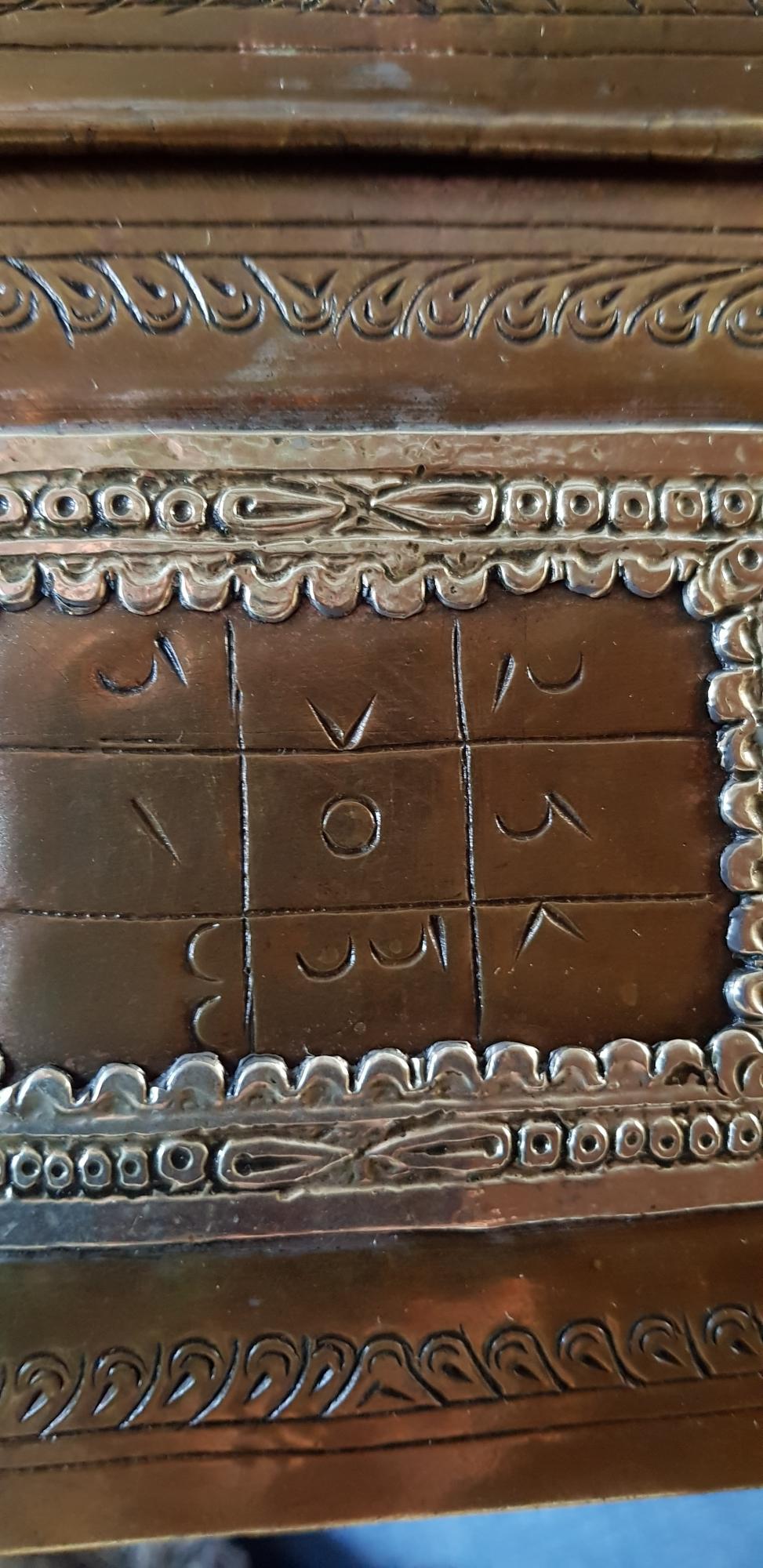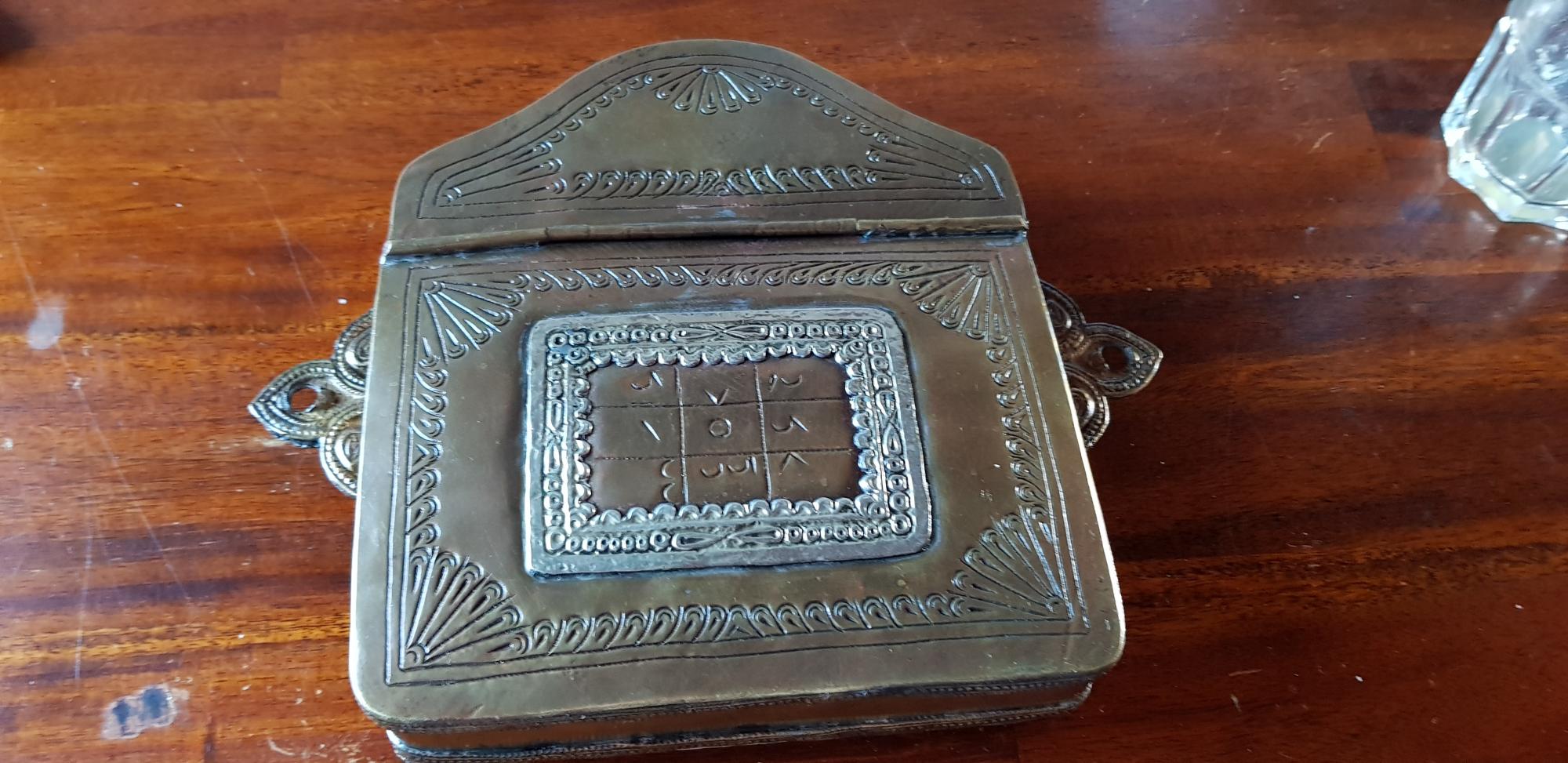
Wer kennt diese Schriftzeichen?
Ich suche jemanden,  der mir bei den Schriftzeichen helfen kann,  welche sich auch einer sehr alten "Box" befinden.  Weiß leider auch nicht so recht, was für ein Gegenstand es ist. Leider konnte ich auch nur diese beiden Bilder mit anhängen.
Leider bin ich nach langer Googlebefragung immer noch keine ansatzweise Lösung gefunden.
Aber vielleicht hat hier jemand eine Idee.
Hier noch zwei weitere Bilder.
Vielleicht helfen diese weiteren Bilder zur Erkennung.
Dieses Gegenstand ist auch von innen verziert mit Blatt und Blumen? Muster.
Ich sehe dort arabische Zahlen …
Hallo, ja das hatte ich auch vermutet,  jedoch fehlen da einige Schriftzeichen.
Das erste Zeichen, es hat noch einen zusätzlichen waagerechten Strich. Dann dieses uu strich. Auch wenn es ne zweistellige Zahl sein soll, was ist dann das 1ste u.
Ich lese dort
672
156
438
Soweit ich weiß, gibt es für die arabischen Zahlen unzählige Schreibweisen, je nach Herkunft, Schreiber, Volksstamm, Sprache und so weiter. Mal so wie es in meinem link dargestellt ist, aber auch gespiegelt, wie die 3 auf deiner Box.
Ralfs Vorschlag, das jemand Arabisch Sprechenden zu zeigen, kann aber sicher für Klarheit schaffen.